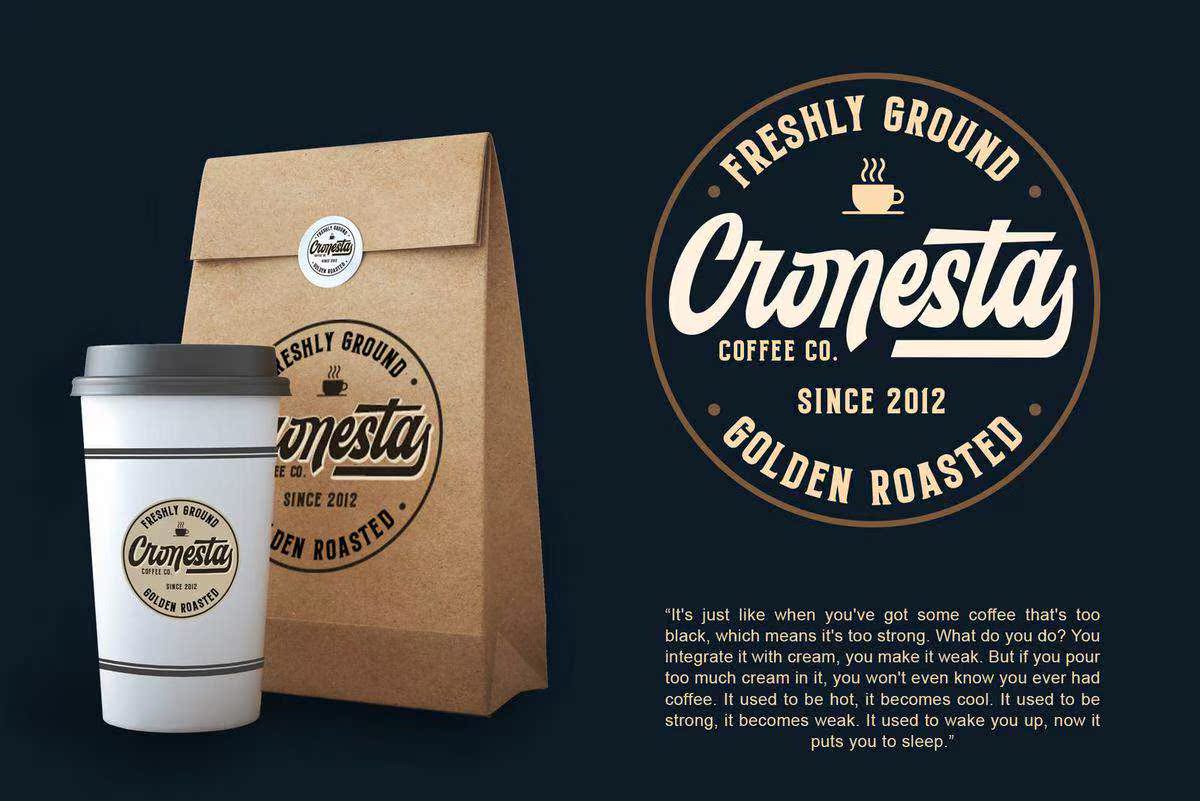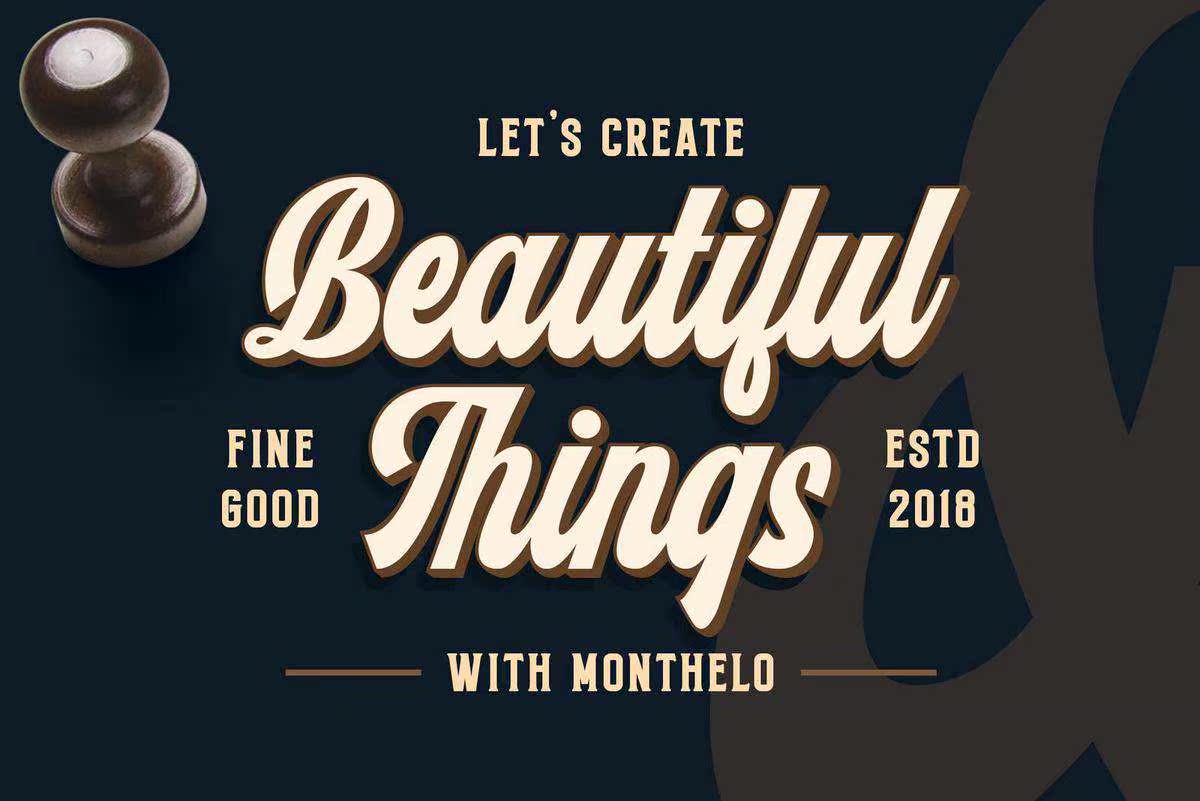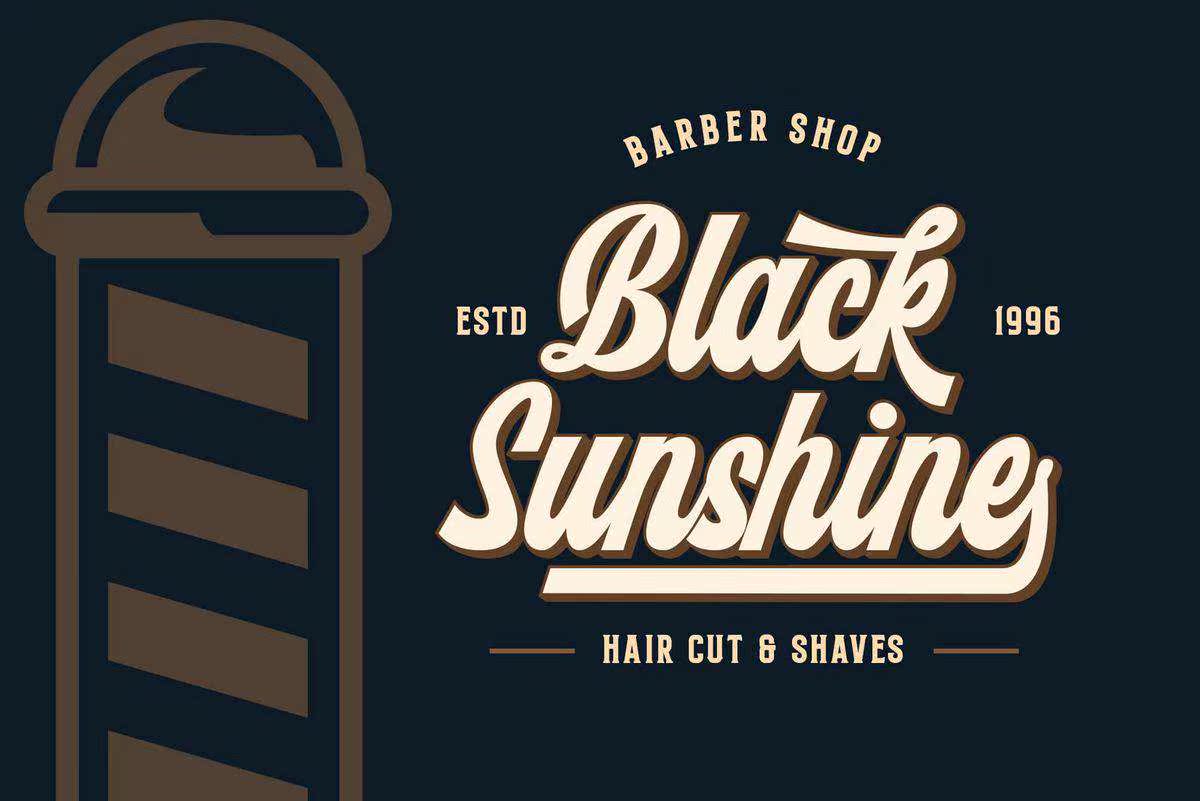
Monthelof不受葡萄酒品牌标志、酒店标志、理发店标志等的影响。Monthelof具有高级印刷,但仍然非常适合现代和古典设计项目。Montelof包括3个变量样式为RegularScript、Exture和Serif。Monthelof具有徽章、标签、T恤设计、品牌、标识、海报、封面、,包装和更多。Monthelof不受葡萄酒品牌标志、酒店标志、理发店标志等的影响。Montelof具有高级印刷,但仍然非常适合现代和古典设计项目。Monteloi包括3个变量样式是RegularScript、Exture和Serif。Monthelof是徽章、标签、T恤设计、品牌、标识、海报、书皮、包装等的完美之选。